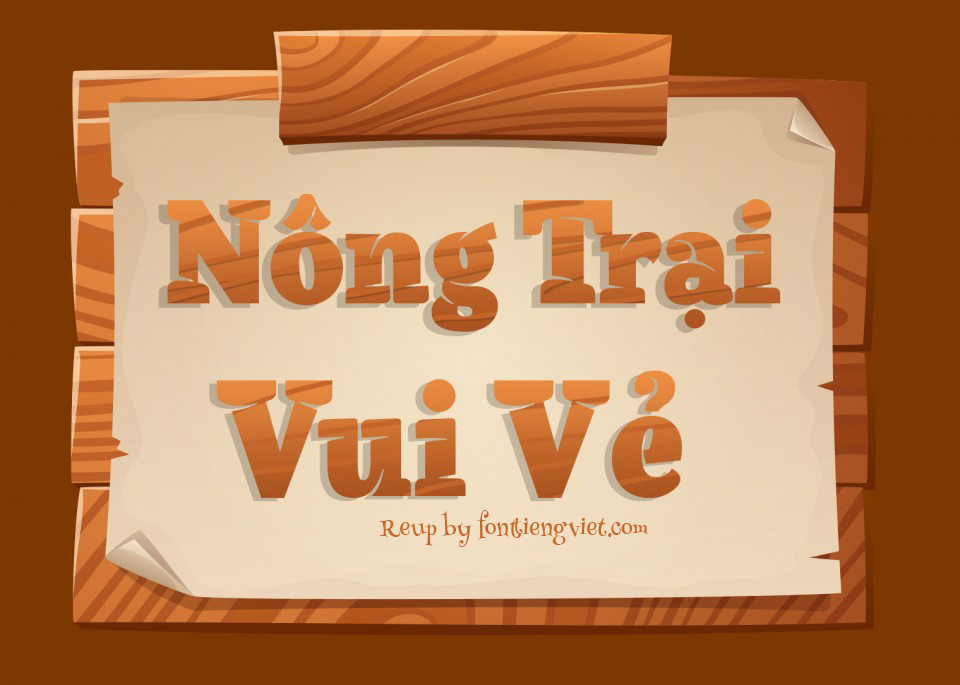
Font việt hóa HLT Fitigraf
Tải Font việt hóa HLT Fitigraf Miễn Phí Cho Thiết Kế Sáng Tạo
Trong thế giới đồ họa hiện đại, việc lựa chọn một bộ Font Miễn Phí chất lượng là yếu tố then chốt giúp sản phẩm của bạn trở nên nổi bật. Font việt hóa HLT Fitigraf nổi lên như một sự lựa chọn hàng đầu nhờ phong cách thiết kế độc đáo, kết hợp giữa nét cổ điển và hơi thở hiện đại. Bộ font này không chỉ đáp ứng tốt về mặt thẩm mỹ mà còn được tối ưu hóa hoàn toàn cho tiếng Việt, giúp người dùng loại bỏ nỗi lo lỗi font khi gõ dấu.
Đặc điểm nổi bật của Font việt hóa HLT Fitigraf
Phong cách thiết kế đặc trưng
HLT Fitigraf sở hữu những đường nét mạnh mẽ, dứt khoát nhưng vẫn giữ được sự tinh tế cần thiết. Điểm nhấn của Font việt hóa HLT Fitigraf nằm ở các chi tiết bo góc khéo léo, tạo cảm giác thân thiện và dễ nhìn. Đây là bộ font cực kỳ phù hợp cho các dự án thiết kế bìa sách, poster sự kiện hay các tài liệu giáo dục cần sự nghiêm túc nhưng không kém phần sáng tạo. Khả năng hiển thị sắc nét trên cả màn hình kỹ thuật số và bản in giúp nó trở thành công cụ đắc lực cho các bạn học sinh và giáo viên.
Tính ứng dụng cao trong học tập
Kết luận về bộ font chất lượng